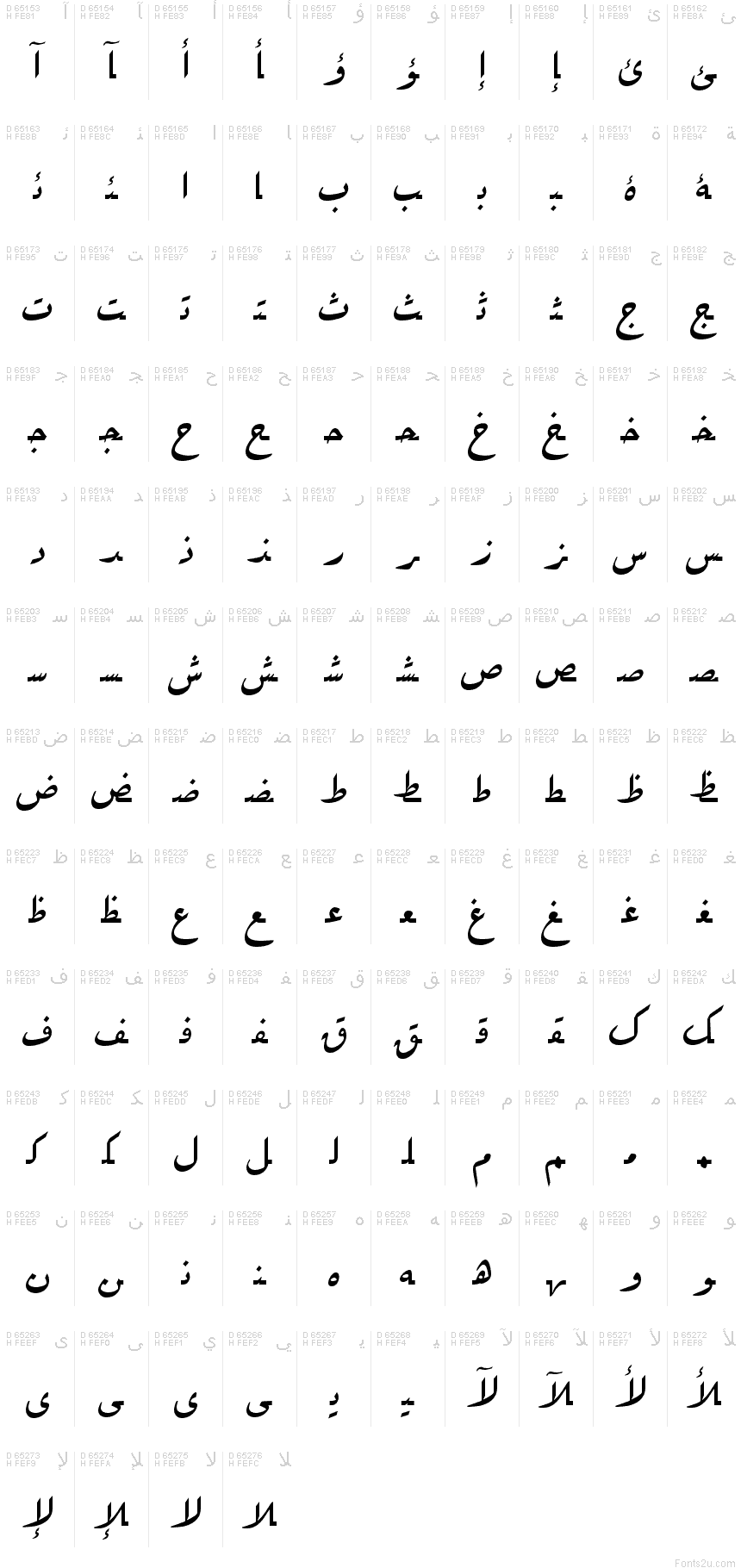
B Sepideh, conçue par Borna Rayaneh, est une police arabe d'affichage gratuite à la silhouette dense et calligraphique, avec un rythme compact, presque emblématique. Les lettres semblent construites à partir de traits larges et sombres qui s'imbriquent étroitement, conférant à l'écriture une allure cérémonielle plutôt qu'un aspect manuscrit décontracté.
Elle convient parfaitement aux affiches culturelles, couvertures de livres, enseignes, cartons de titres et aux projets de branding où la typographie porte l'essentiel de l'ambiance. En tant que police gratuite, B Sepideh excelle dans les mises en page courtes et les titres évoquant des monogrammes, car ses formes imbriquées créent un bloc de texture puissant qui se lit autant comme une image que comme du texte.